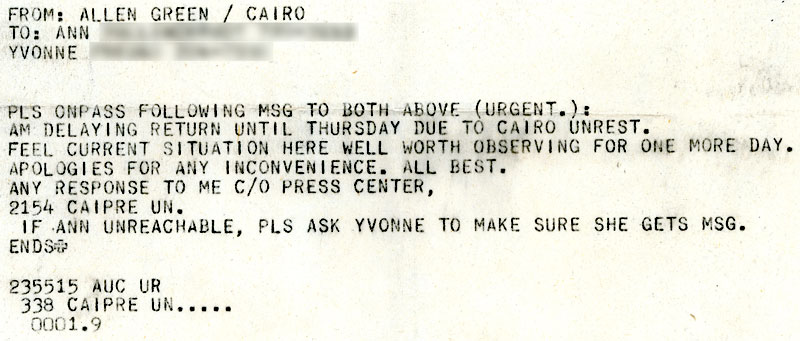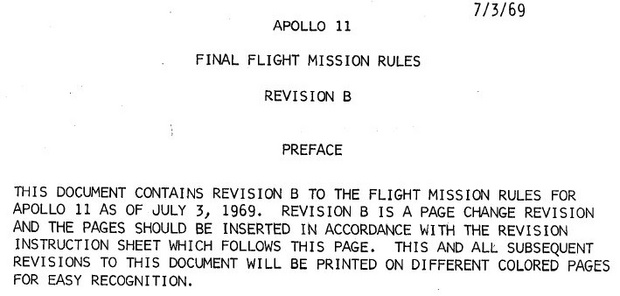
Nochmal NASA: serifenlose Schreibmaschine
Aus den Mission Rules (PDF, 11MB):
Puh, so eine habe ich noch nie gesehen.:-?Vielleicht bringt eine Anfrage direkt bei der Nasa Aufschluss? Laut Kollege Minimalist scheinen die dem interessierten Publikum gegenüber auf ihrer Website ja ganz aufgeschlossen zu sein.
Ich glaub nicht, dass das einer Schreibmaschine entspringt, dafür sind die Buchstaben zu unterschiedlich. Zum Beispiel das C in DOCUMENT ist anders als die anderen … Kann das einem Telex oder was auch immer entstammen? Dein link zu den Mission rules funktioniert ja leider nicht … [edit] hab aber einen gefunden. Das Dokument ist ja so zusammenkopiert und -gestückelt, dass das durchaus einem Telex entspringen könnte.
Einfach mal wild nach "Telex USA 1970 gegoogelt":